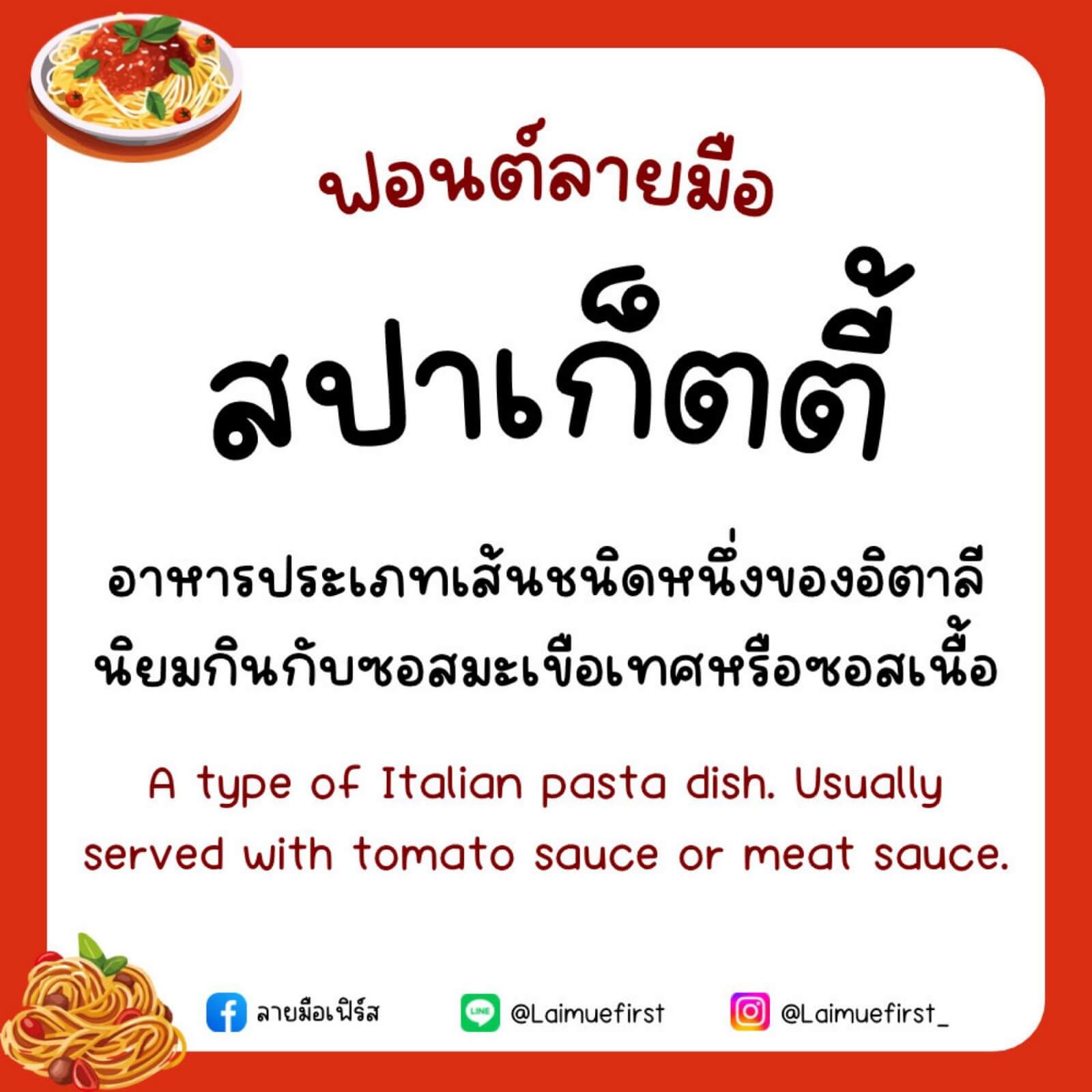
เฟิร์ส (First)
ฟอนต์ First ฟอนต์น่ารัก อ่านง่ายสบายตา ใช้เพื่อเพิ่มความน่ารักให้โน้ตหรืองานต่างๆ ให้น่ารักและอ่านได้สบายตามากขึ้น แจกฟรีไปเลยสำหรับฟอนต์ลายมือเวอร์ชันทดลอง ใช้ได้เฉพาะแบบส่วนตัว เช่น ตกแต่งสมุดโน้ต จดงานต่างๆ ขอบคุณทุกคนที่ผ่านมาสนับสนุนนักศึกษาตัวน้อยๆ นะค้าบ